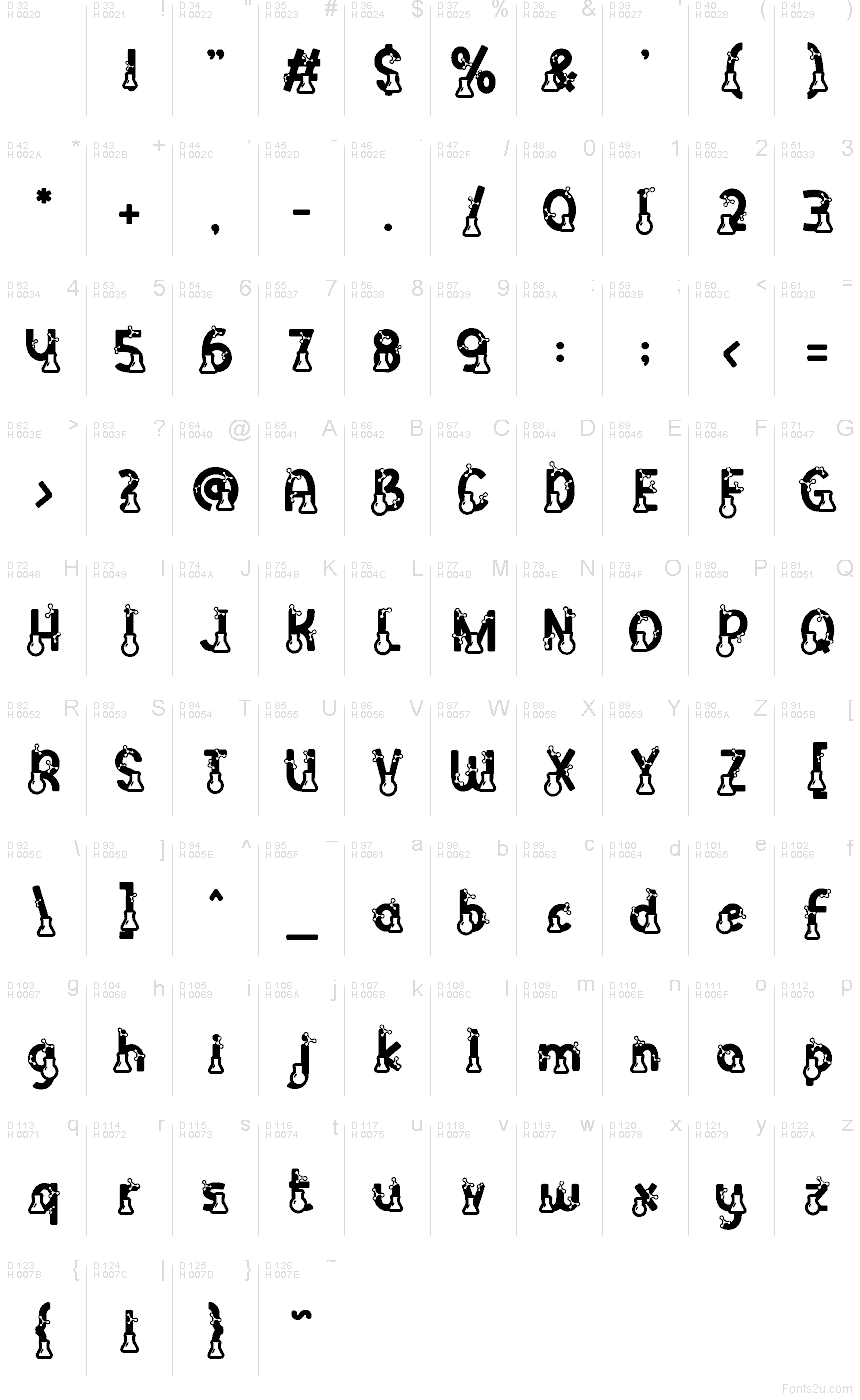
Clever Science Tube
Clever Science Tube von Putracetol Studio ist eine kostenlose Display-Schriftart im Labor-Look, deren Buchstaben an Bechergläser, Kolben und sprudelnde Reagenzgläser erinnern. Das Alphabet setzt auf eine verspielte Chemie-Atmosphäre: Markante schwarze Formen treffen auf weiße Glashohlräume und kleine, sich wiederholende Tröpfchen, die sich durch jeden Buchstaben ziehen.
Sie passt perfekt auf Plakate für STEM-Clubs, Flyer für Kinder-Workshops, Schilder für Schulveranstaltungen, wissenschaftliche Verpackungen und YouTube-Thumbnails, bei denen eine auffällige Schrift mit echtem Experimentier-Charakter schnell ins Auge fallen soll. Verwenden Sie sie für kurze Titel, Logo-ähnliche Überschriften oder Einblendungen, denn die Glas-Silhouetten und Blasen-Details vermitteln das Thema, noch bevor man viele Worte liest.